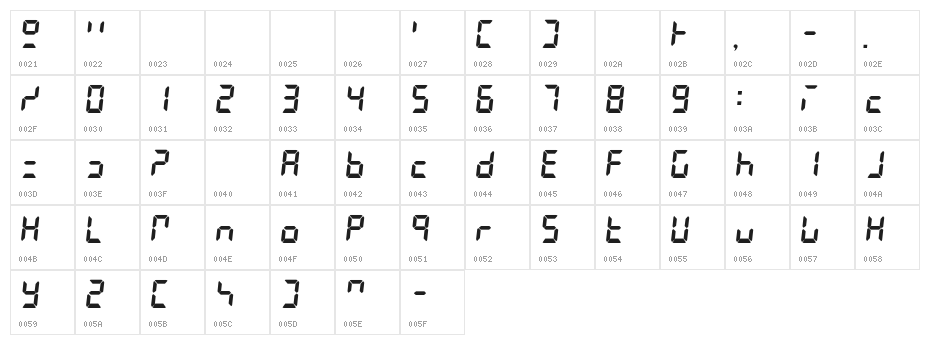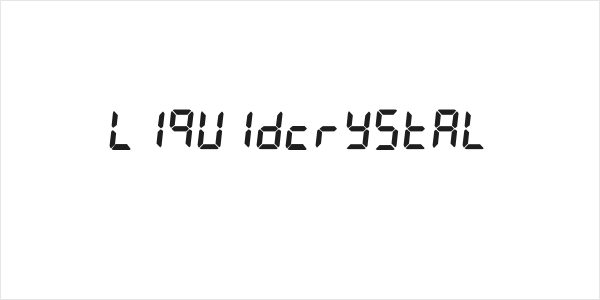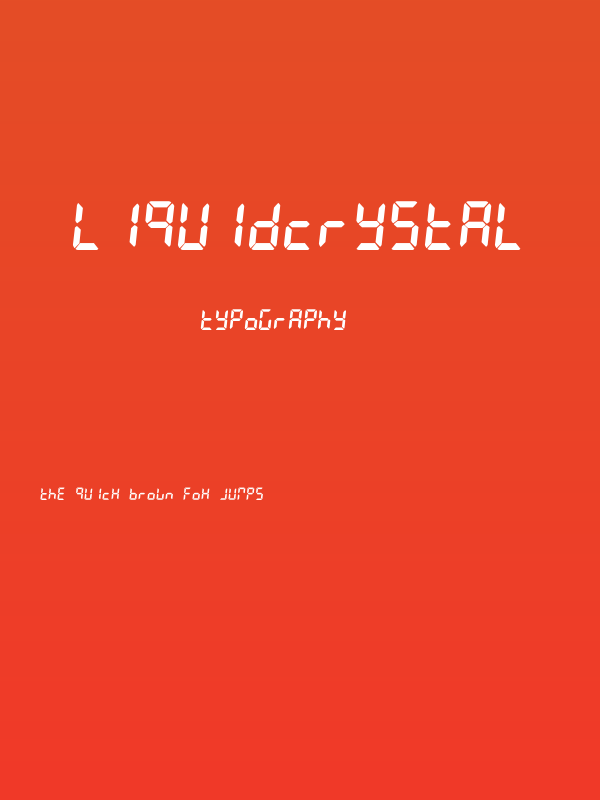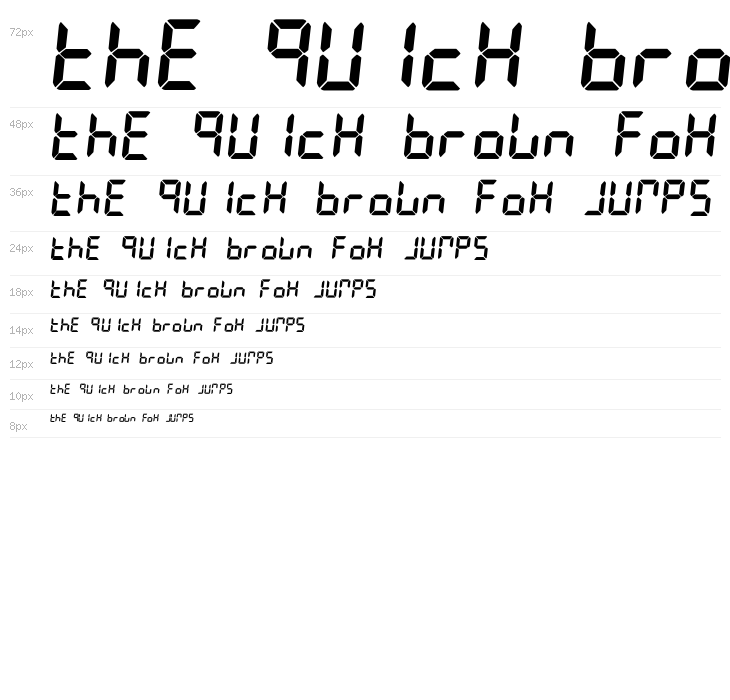
LiquidCrystal Font
| Caso d'uso | Headlines, Digital displays, Tech branding |
| Progetti proposti | Ideal for digital interfaces, tech-themed designs, electronic device displays, and futuristic branding. |